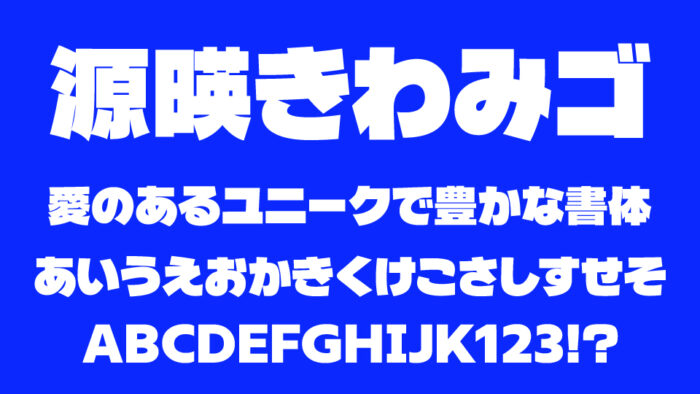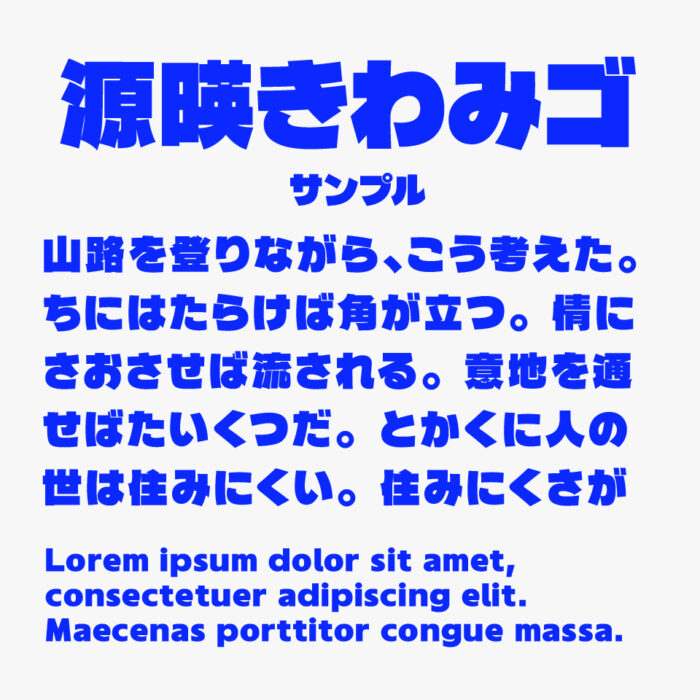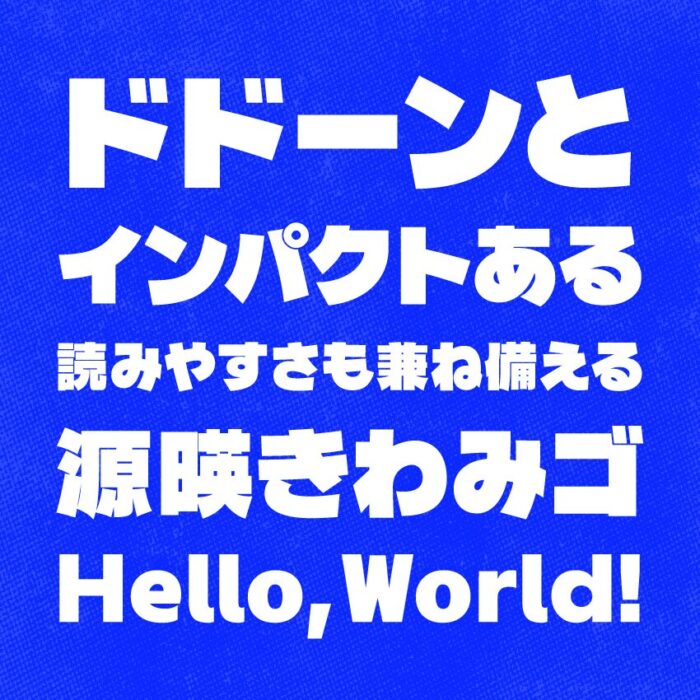
源暎きわみゴ
源暎きわみゴフォントは、「デラゴシック」フォントをベースに、オリジナルかな文字・英数字に置き換えて制作された超極太のゴシック体フォントです。
デラゴシックに比べて、線に強弱や勢いが抑えられて作られていますが、ダイナミクス感やインパクトはきちんと継承されており、かつ視認性や判読性も高くなっている素敵なフォントです。
強い印象があり、目を引くフォントなので、サムネイルやテロップなどにさまざまな場面で活躍できるフォントです。